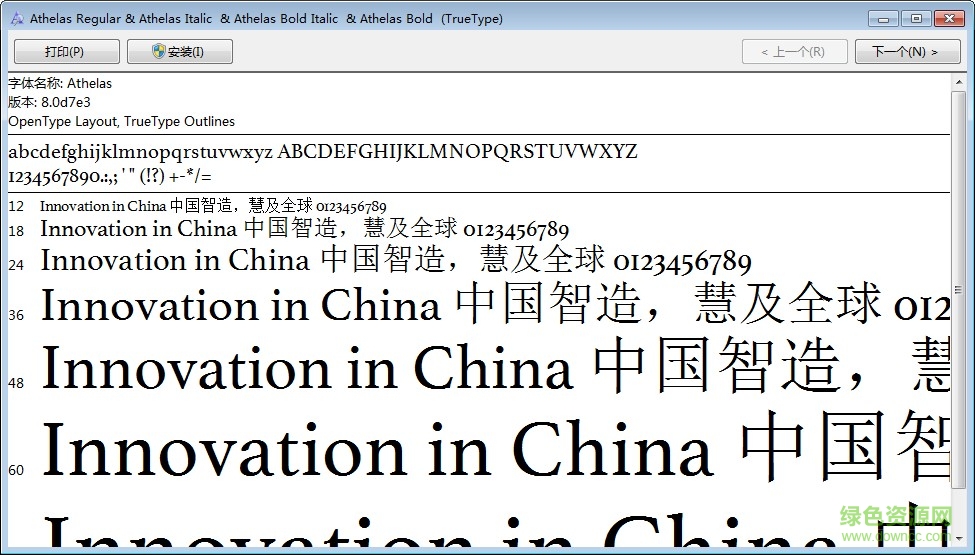
athelas regular
athelas regular字體是一款極具美感的英文字體,筆觸輕柔,點(diǎn)畫適宜,字體線條如游絲般流動,流暢舒展,神采奕奕,喜愛的小伙伴們快來下載收藏吧!
athelas regular字體簡介:
字體風(fēng)格非常獨(dú)特,筆畫輕盈,點(diǎn)畫精致,轉(zhuǎn)折十分舒展嗎,常常用于各類海報(bào)、雜志、書刊或廣告中!